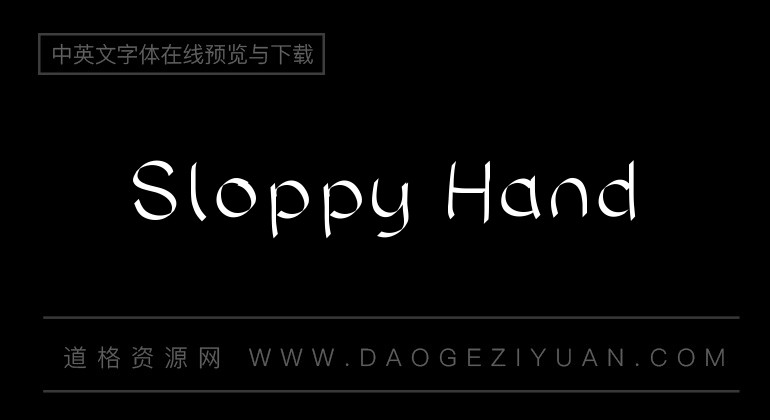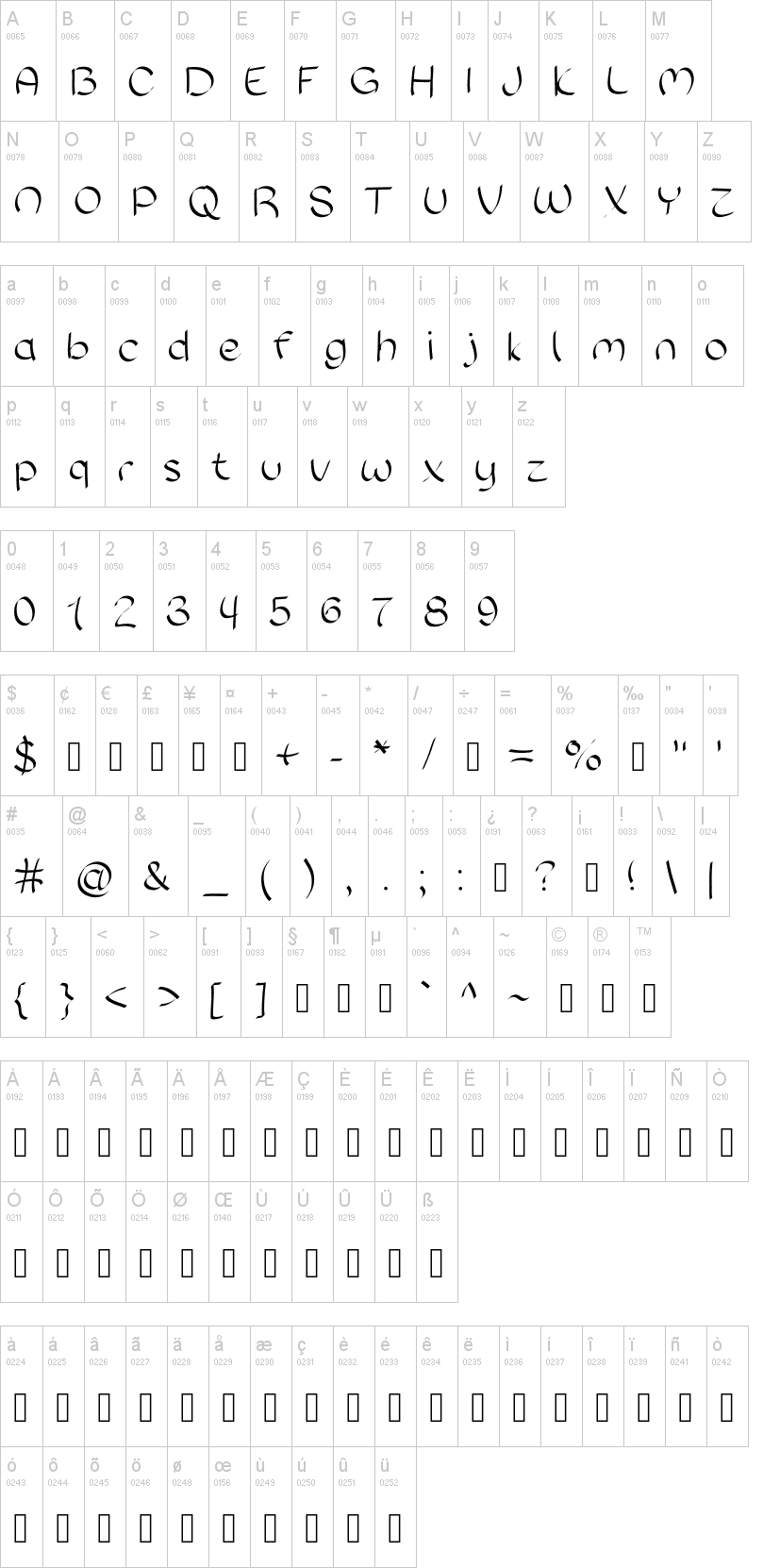
? Sloppy Hand是一款手写体字体,由美国设计师Gerald Gallo创作。它的特点是模糊而不失细节,显得温暖而又有趣,适合用于标题、标识、卡片等场景。它具有较强的表现力和自然的外观,能够传达出温暖、友好、轻松的氛围。内容介绍
Sloppy Hand是一款非常不错的手写艺术字体,具有很好的视觉感,适合于文化类的宣传设计、商业类品牌的广告和产品包装设计以及个性化文字排版等较多场景。